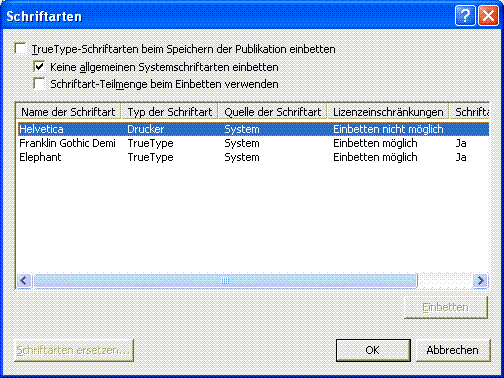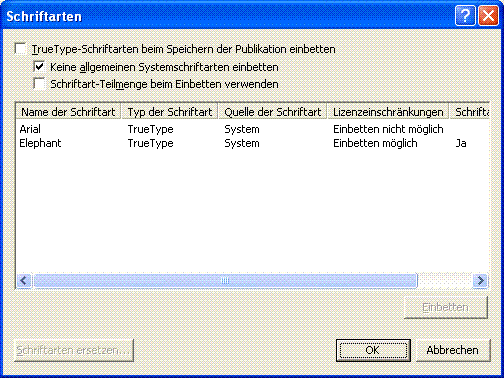
Publisher 2002 "verliert" Schriftart Helvetica
Ich habe hier bei der Arbeit ein kleines Prob mit dem Publisher 2002. ich habe heute morgen eine Visitenkartevorlage mit der Schriftart Helvetica gemacht, und wollte diese heute Nachmittag noch für andere Mitarbeiter anpassen. doch wenn ich die Datei öffne kommt untenangehängte Meldung.
Weiss jemand wie man dieses Problem lösen kann?
...Weiss jemand wie man dieses Problem lösen kann?
Hast schon mal versucht zu testen, ob die Schrift überhaupt eingebettet werden kann?
Wenn nicht, versuche folgendes:
[font=&quot]Gehe im Menü Extras auf Tools für den professionellen Druck, und klicke auf "Schriftarten". Dann überprüfe unter "Schriftart einbetten" die Informationen, ob die Schrift überhaupt eingebettet werden kann. Wenn die Option „Einbetten möglich“ aktiviert ist, kannst Du die Schriftart einbetten. Wenn eine der Optionen „nur Vorschau“ oder „Einbetten nicht möglich“ aktiviert ist, kannst nur die Schriftart durch eine andere ersetzen.
[font=&quot]Und dann solltest Du drauf achten, wenn Du ein Dokument öffnest, daß eingebettete Schriften verwendet, erscheint ein Dialogfeld "Schriftarten laden". Dieses musst Du mit "Ok" bestätigen.
[font=&quot]Noch 'ne Frage: Ist denn Helvetica in Deinem Fonts-Ordner des BS installiert?
also ich hab dir ein Screen angehängt. Screenshot 1
Das komische ist, in einem bestehenen Dokument ist die Helvetica Schrift nicht verfügbar. Aber mache ich zum Beispiel eine neue Publikation (neue Datei) kann ich diese ohne Probs anwählen. Hab aber gerade gesehen, dass bei der neuen Datei bei diesen Einbetten steht : "einbette nicht möglich" Siehe Screenshot 2
Zudem ist diese Schrift nicht (nicht mehr) in Windows Fonts verzeichnis.
Also siehts schlecht aus, oder wie siehst du das?
Zudem ist diese Schrift nicht (nicht mehr) in Windows Fonts verzeichnis.
Also siehts schlecht aus, oder wie siehst du das?
Schriften mit hervortretenden Serifen werden "Serifenbetonte Schriften" oder "Antiqua Schriften" genannt. Im Vergleich dazu haben Serifenlose Schriften keine Endstriche. Die Schriften Helvetica, Verdana und Lucida Sans Unicode sind Serifenlose Schriften, die auch Grotesk-Schriften genannt werden.
Also, das Problem, was ich nach meiner Auffassung jetzt sehe, ist wohl folgendes:
In der Windows Welt heißt Helvetica Arial, da Microsoft ähnlich wie im Fall der Zapf Dingbats keine Lizenzgebühren zahlen wollte. Helvetica und Times sind zwei Zeichensätze (auch PostScript) die häufig zusammen eingesetzt werden. Bei eigenen Texten sollte man vor dem Einsatz Alternativen testen
In Folge dessen, wirst Du die auch auf Deinem Rechner so nicht finden.
Wir machens jetzt einfach so, dass wir eine andere Schriftart genommen haben (arial) und damit funktionierts...